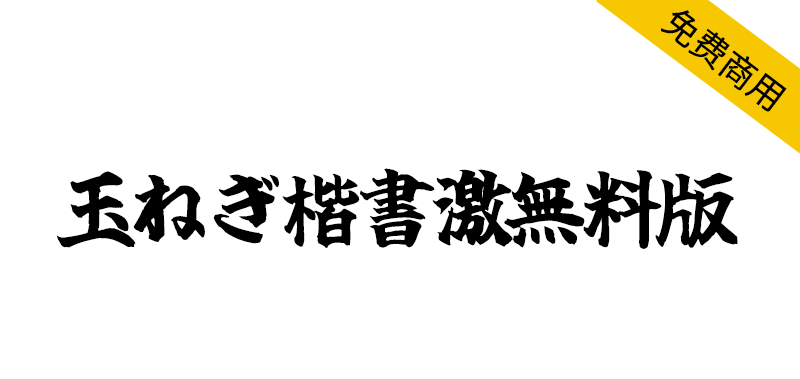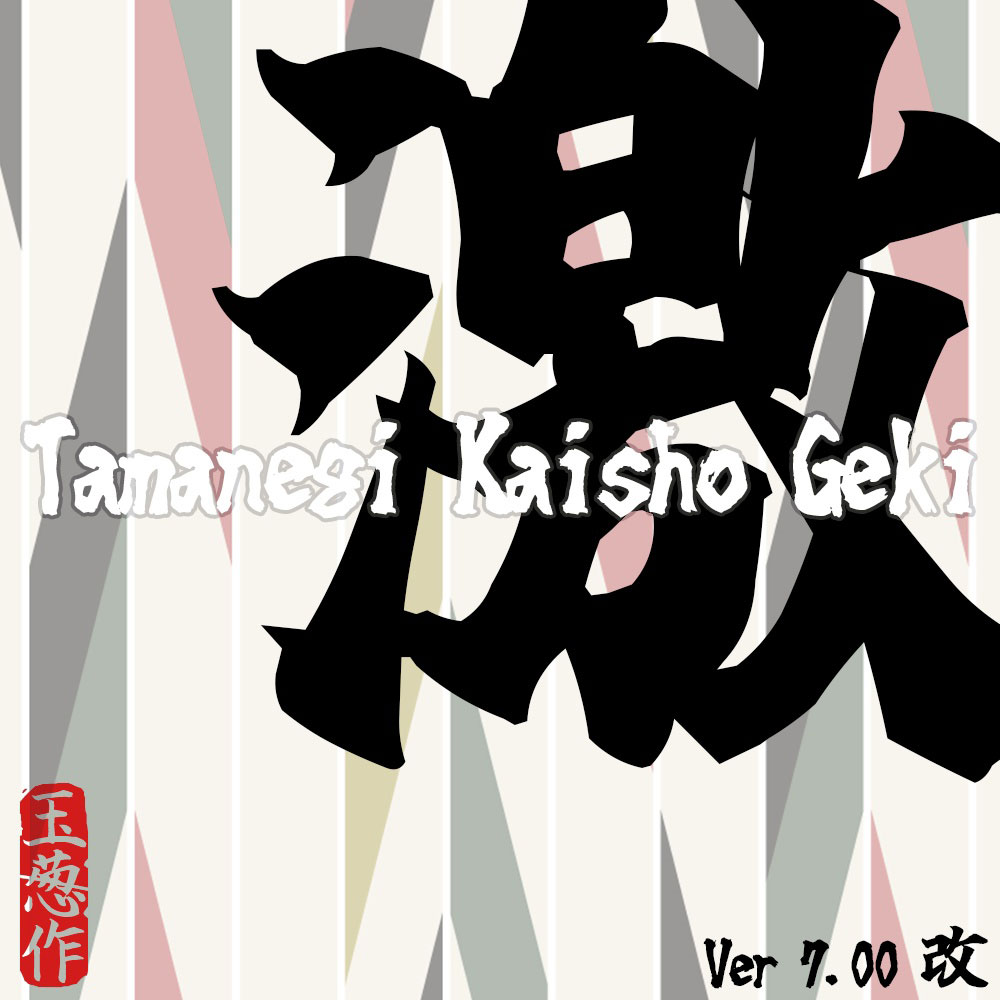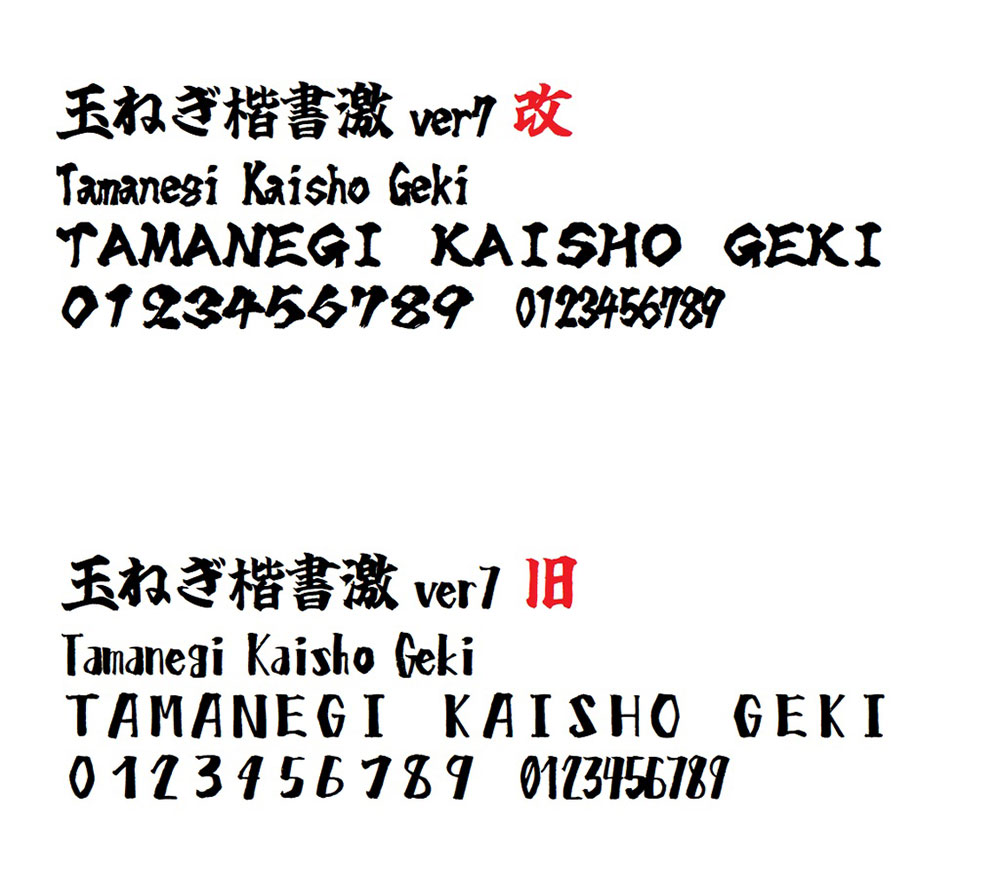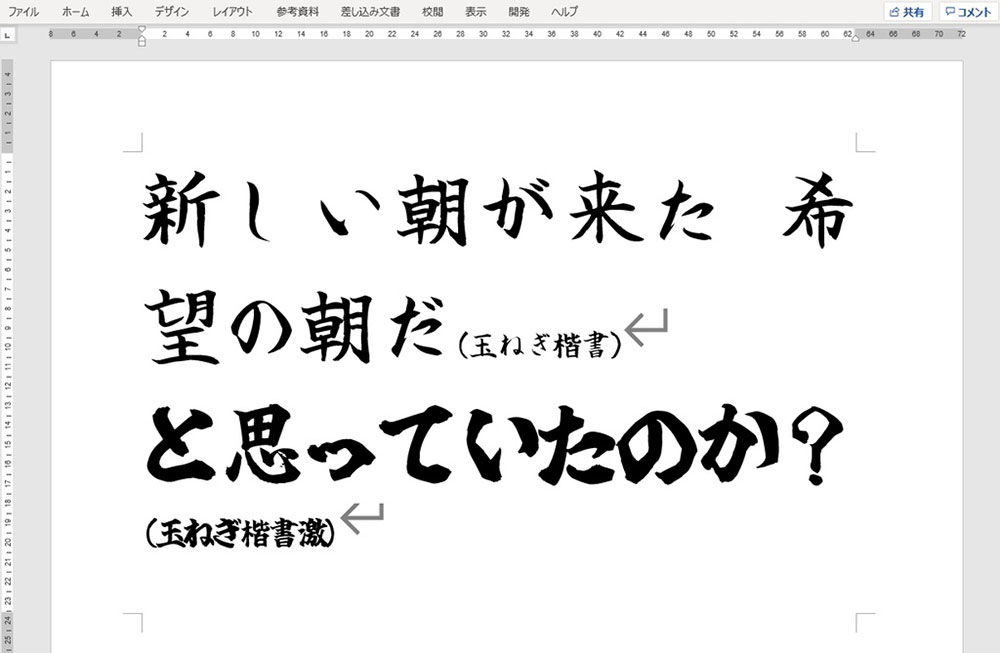
玉ねぎ楷書激無料版是通过使用武藏系统 (http://opentype.jp/) 的手写字体创建的。是为动画、同人志、贺年卡等场景制作的简单手写毛笔字体洋葱楷书(ttf形式)有点激烈。
本ファイルは武蔵システム(http://opentype.jp/)の 手書きでフォント を使って作成しました。動画・同人誌・年賀状などあらゆる創作の場面を想定して作られたシンプルな手書き毛筆フォント玉ねぎ楷書(ttf形式)をちょっと激しくしたものです。